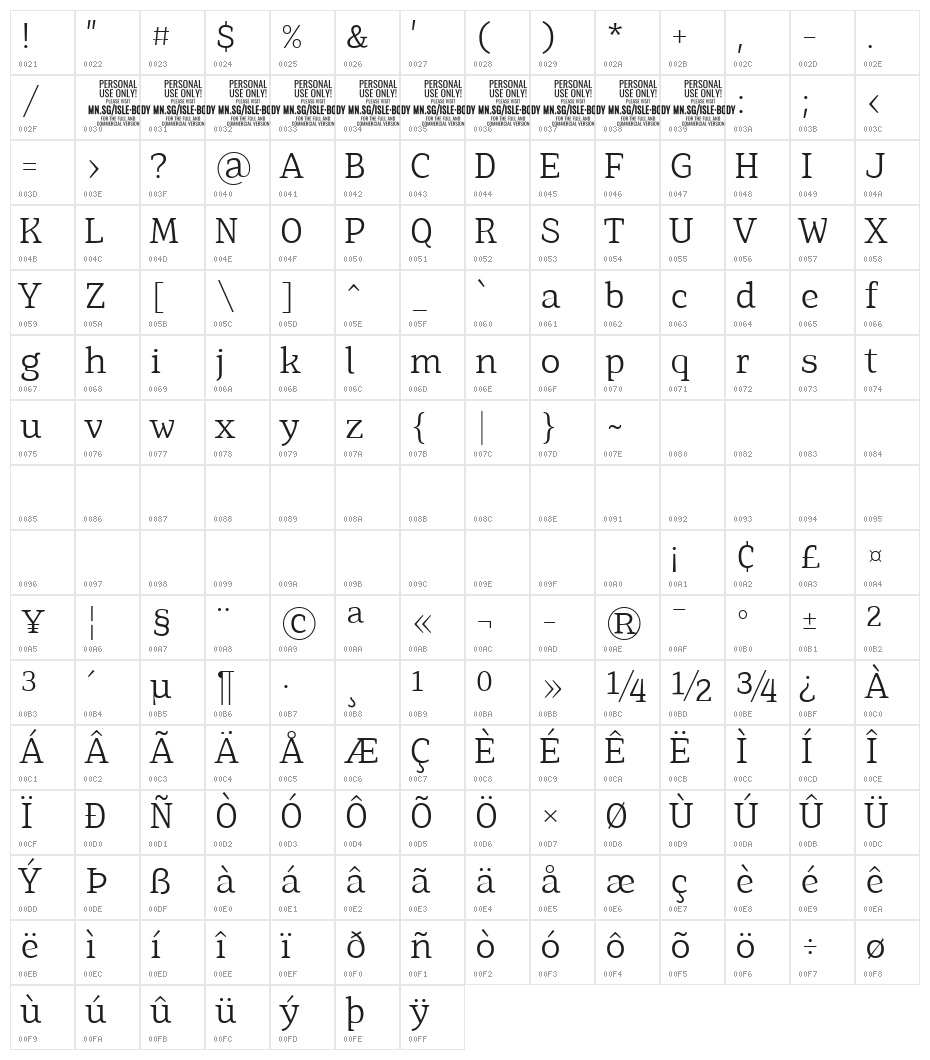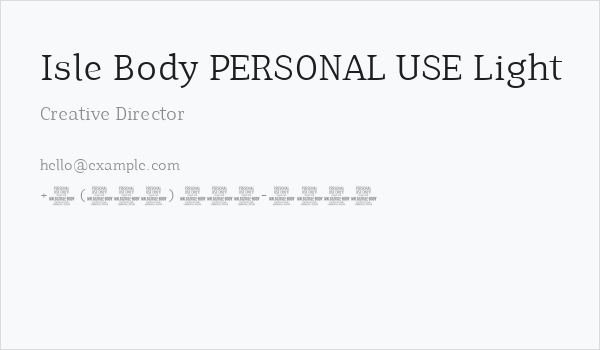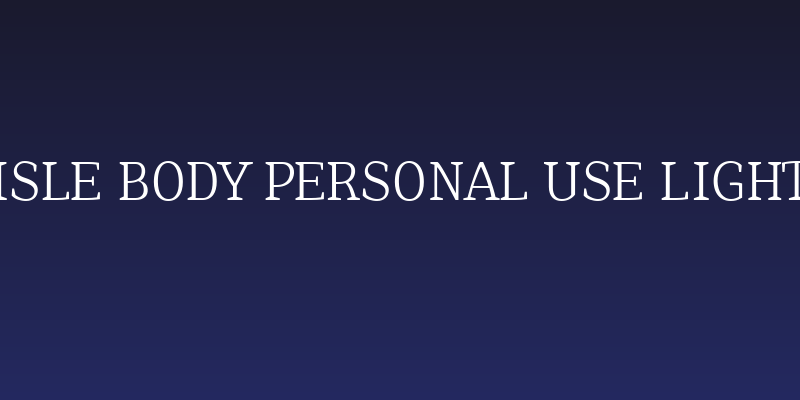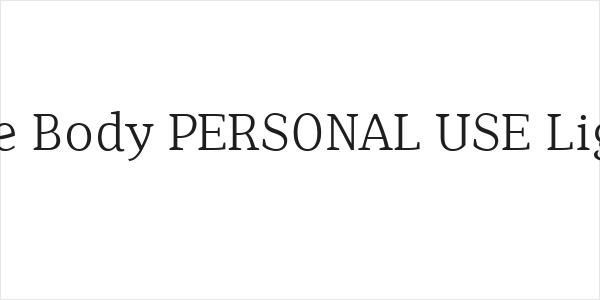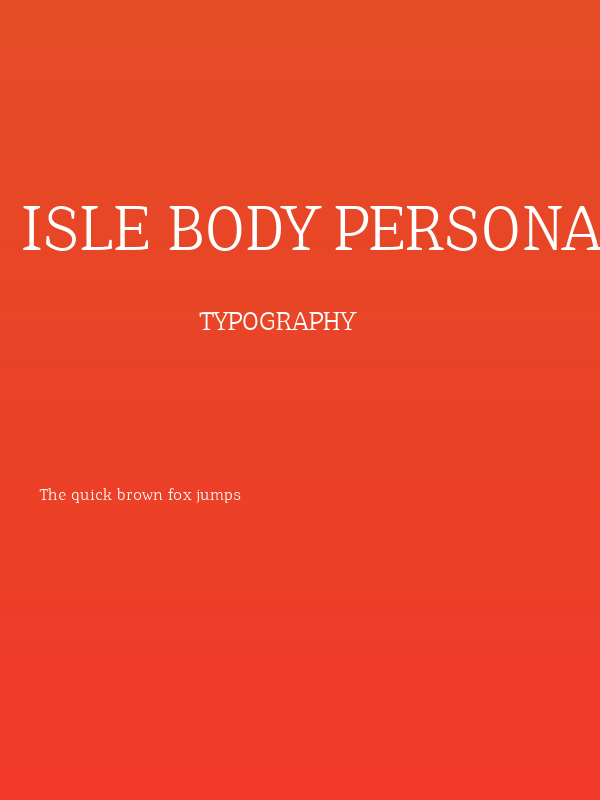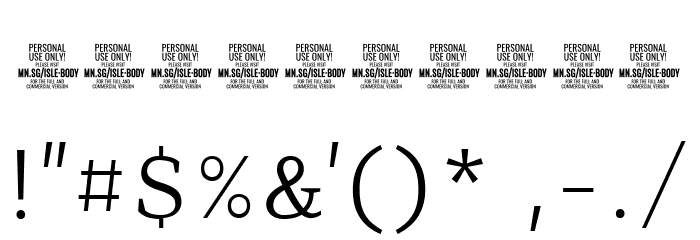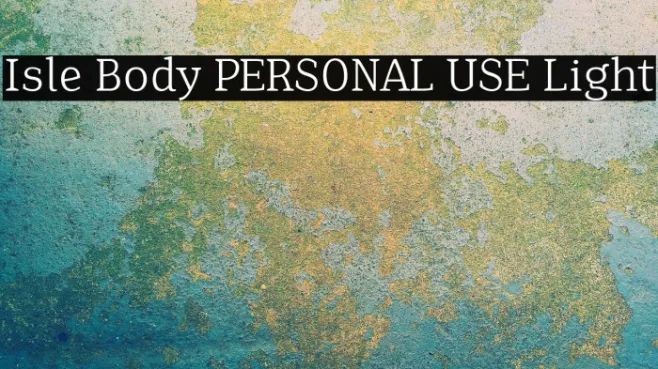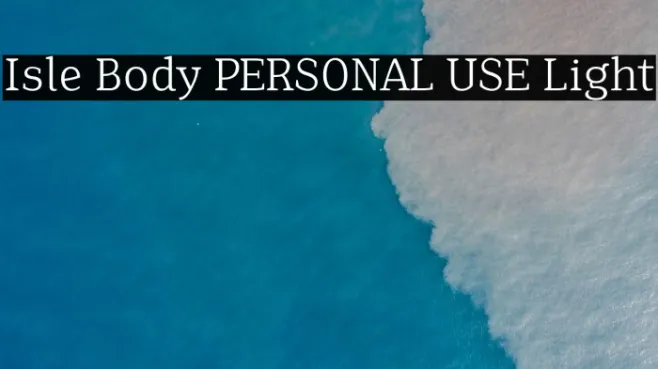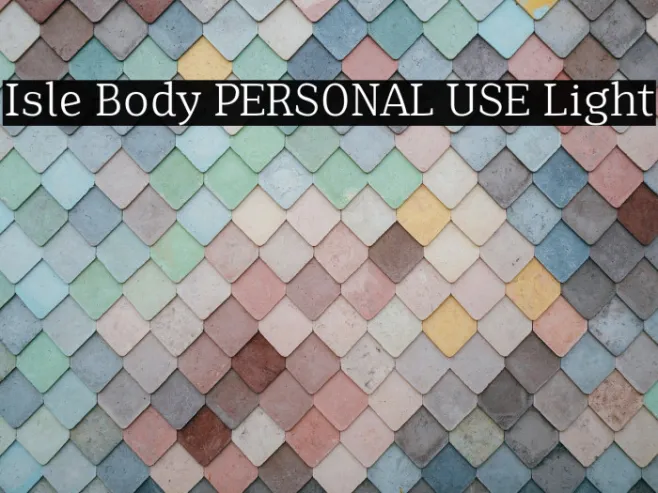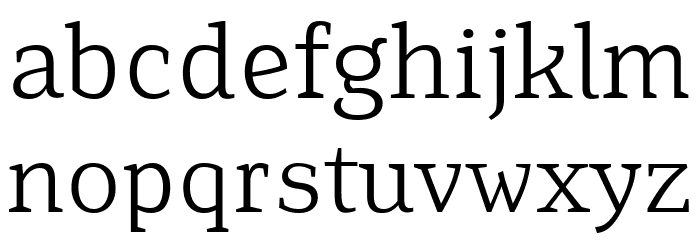
Isle Body PERSONAL USE Light Font
| Estilo general | Classic |
| Caso de uso | Body text, Headlines, Editorial design |
| Proyectos propuestos | Ideal for editorial design, book covers, elegant invitations, and branding projects. |